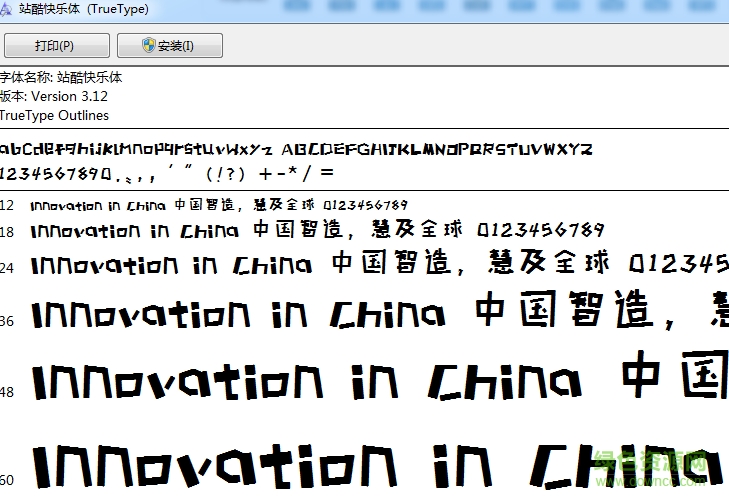
happyzcool字體是一款純手寫的個性字體,該字體個性分明,非常具有特點,別具一格的排版,吸引了許多用戶,有喜歡的朋友就趕快來綠色資源網(wǎng)下載使用吧!
happyzcool字體是一款個性英文字體,字體飄逸的寫法,給用戶帶來別樣的精彩體驗,有需要的朋友就趕快來綠色資源網(wǎng)下載吧!